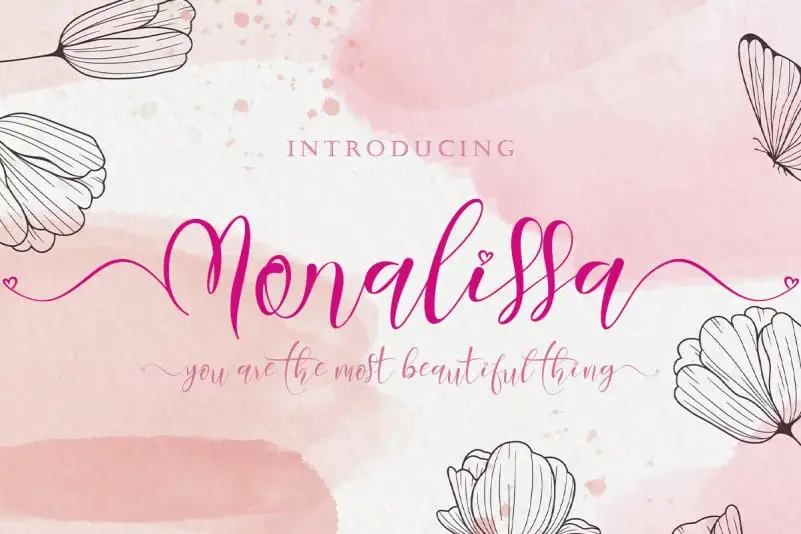
Monalissa Calligraphy Font – Fonte Grátis
Monalissa Calligraphy Font
A Monalissa Calligraphy Font é uma deliciosa escolha para quem busca uma tipografia elegante e delicada. Este font não apenas adiciona beleza a seu trabalho, mas também eleva-o a um nível superior de sofisticação e refinamento. É especialmente adequado para marketing de produtos, promoção de negócios, criação de citações, celebração de casamentos, cartões de convite, logotipos, branding e atualizações na mídia social. Além disso, é uma excelente opção para decorar momentos especiais e outros projetos que você tenha. Escolha a Monalissa Calligraphy Font e transforme qualquer projeto em algo realmente especial.